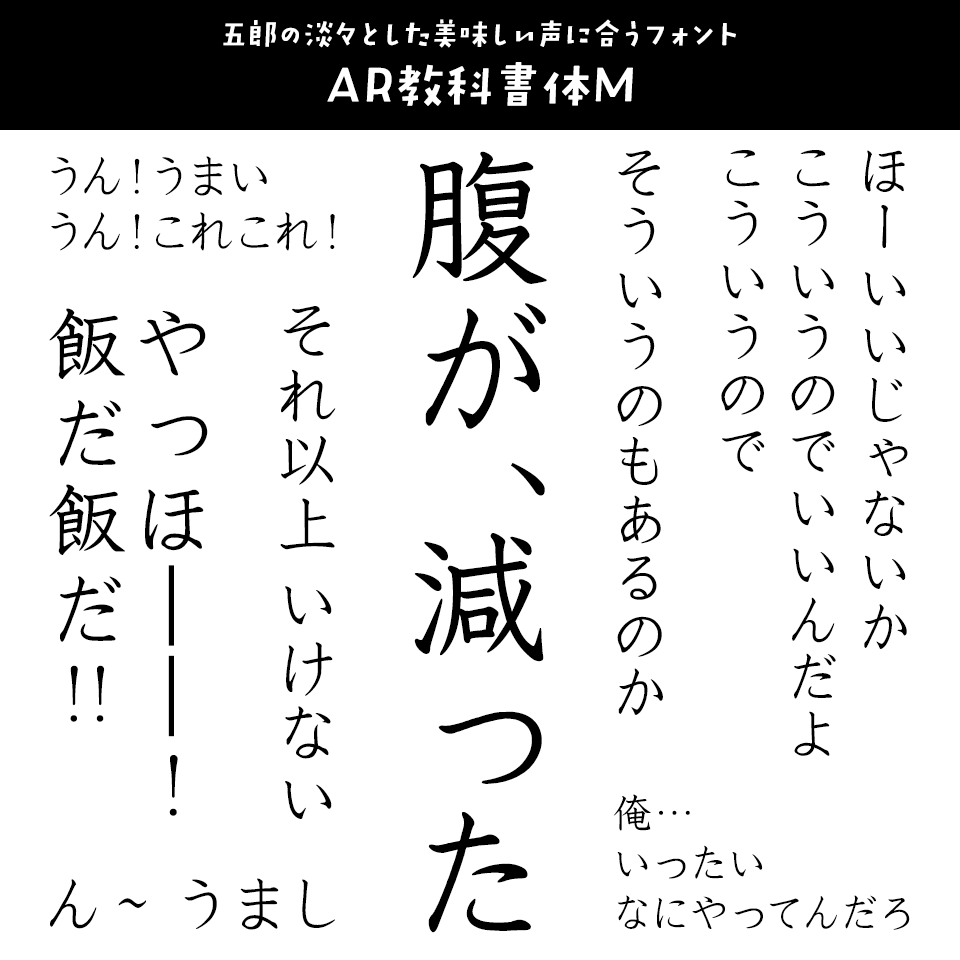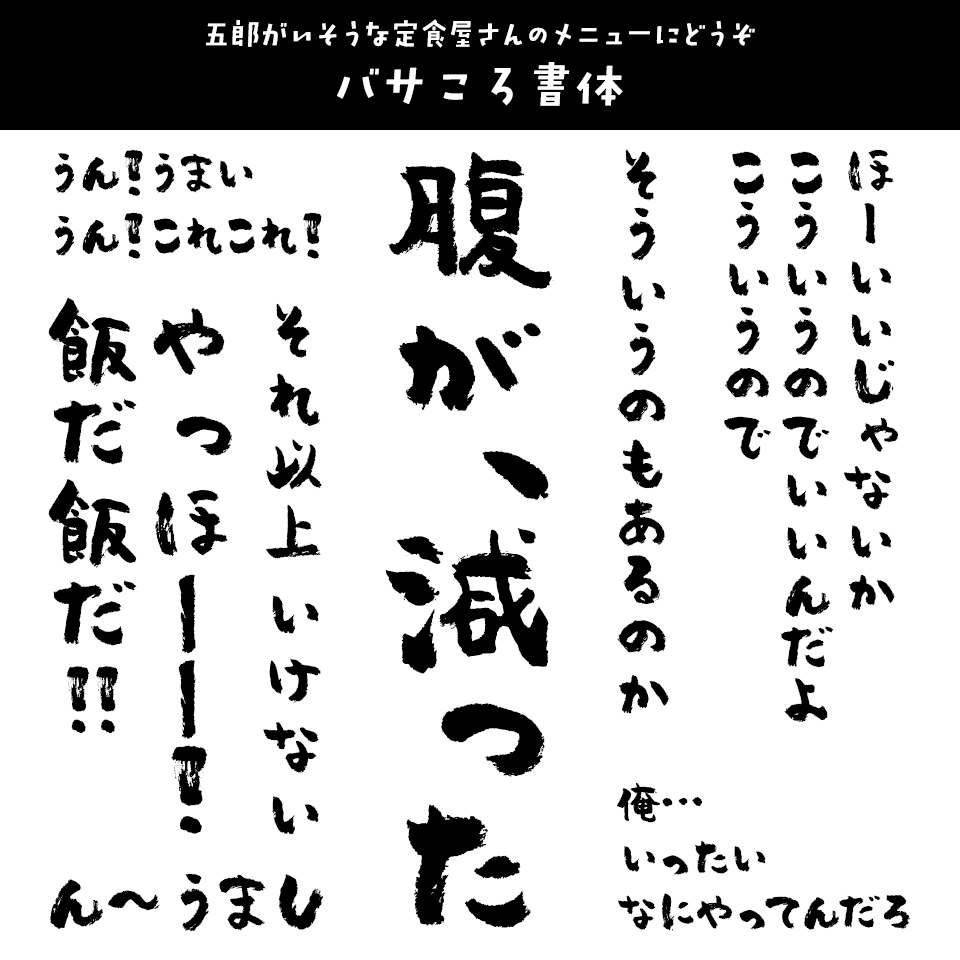
「孤独のグルメ」に合うフォント:特化型 目的別フォントガイド #116
今回は「孤独のグルメ」に合うフォント。日々フォントのことばかり考えている当店スタッフが直感的に選んだフォントをご紹介します。
「孤独のグルメ」に合うフォントをスタッフが選びました
「孤独のグルメ」に合うフォント ヒラギノ明朝 W3
コミックスで五郎の心の声で使われる明朝体
ヒラギノ明朝 W3【ヒラギノフォント】
「孤独のグルメ」に合うフォント ヒラギノ明朝 W3
現代的でシャープな表情の中に、伝統的な筆文字の美しさをマッチさせた華やかで上品な書体。起筆、送筆、収筆(とめ、はね、はらいなど)の各部に美しい筆づかいを取り入れつつ、日常的に使えるベーシックな明朝体として、デジタルならではの緻密さと一貫したデザイン性を持つ渾身の明朝体。
「孤独のグルメ」に合うフォント AR教科書体M
五郎の淡々とした美味しい声に合うフォント
AR教科書体M【アーフィック】
「孤独のグルメ」に合うフォント AR教科書体M
教科書でよく使用される、明朝体と楷書体の中間のデザイン。筆書きの楷書体に近く、明朝体のようにハネやはらいがありますが、線の太さの強弱は弱く、視力の弱い人にも見やすく読みやすい書体です。
「孤独のグルメ」に合うフォント マティス
力強いモノローグに
マティス【フォントワークス】
「孤独のグルメ」に合うフォント マティス
独特の重厚感のあるフォントでモノローグにもっと力強さと説得力を追加してみませんか。
「孤独のグルメ」に合うフォント DF唐風隷書体 W5
やや角ばった形の中にも素朴さが溢れだすフォント
DF唐風隷書体 W5【ダイナフォント】
「孤独のグルメ」に合うフォント DF唐風隷書体 W5
唐風隷書体 は、太く横長で扁平な字形が安定感をもたらし、中華風や古典的な雰囲気を演出するのにぴったりです。
「孤独のグルメ」に合うフォント DFクラフト遊 W5
どこかほのぼのとした印象の五郎の声に合う書体
DFクラフト遊 W5【ダイナフォント】
「孤独のグルメ」に合うフォント DFクラフト遊 W5
遊び心にあふれる子供が書いた文字をイメージしてデザインされた書体です。その為、文字のユニークさや破調が表現されたかわいらしい印象の書体になりました。短い点や線で構成された字形は軽やかさを感じさせ、陽気で活発な雰囲気が一層、引き出されています。
「孤独のグルメ」に合うフォント DFクラフト墨 W9
独特のこだわりを持つ五郎のセリフにぴったりの筆文字書体
DFクラフト墨 W9【ダイナフォント】
「孤独のグルメ」に合うフォント DFクラフト墨 W9
書道元来の構成や書き方に変化を加え、文字の面白さや破調を表現した書体です。線の長さや「へん」「つくり」などの部首に字形を崩す程の変化を加えました。また、空間の取り方も独特であり、丸く豊かな運びによって可愛く、リラックスした雰囲気を引き出され、ストロークからは墨字の躍動感が表現されています。
「孤独のグルメ」に合うフォント バサころ書体
五郎がいそうな定食屋さんのメニューにどうぞ
バサころ書体【昭和書体】
「孤独のグルメ」に合うフォント バサころ書体
かすれのあるゴロっとしたフォルムが温かみや親しみやすさを感じられる堅すぎない筆文字です。
「孤独のグルメ」に合うフォント 心龍爽
五郎と同じで細身で骨太
心龍爽【昭和書体】
「孤独のグルメ」に合うフォント 心龍爽
細めながらもしっかりとした毛筆体で、五郎のスタイルを連想させます。
「孤独のグルメ」に合うフォント DS筆七七
大衆食堂の雰囲気漂う筆文字風フォント
DS筆七七【七種泰史/デザインシグナル】
「孤独のグルメ」に合うフォント DS筆七七
粋な下町のオヤジさんのようなイメージをもって制作された書体。庶民的で温もりのある筆文字風フォントです。
「孤独のグルメ」に合うフォント 筆シリーズ TA筆くろもん
大衆食堂にありそうな手書き風フォント
筆シリーズ TA筆くろもん【スキルインフォメーションズ】
「孤独のグルメ」に合うフォント 筆シリーズ TA筆くろもん
あたかも誰かが手書きしたような少し崩れたリアル感が楽しい手書き風フォント。ゴシックデザイナー鈴木竹治のフォント。
「孤独のグルメ」に合うフォント 馬王顔書
手書き風だけどグイグイくる
馬王顔書【六葉情報】
「孤独のグルメ」に合うフォント 馬王顔書
五郎の心の声と同じで、控えめだけど主張の強い手書き風筆文字です。
「孤独のグルメ」に合うフォント 手書き屋本舗 竹ぱんだ
温かみのある手書き風フォント
手書き屋本舗 竹ぱんだ【スキルインフォメーションズ】
「孤独のグルメ」に合うフォント 手書き屋本舗 竹ぱんだ
強弱のついた手書きフォント。穏やかで五郎の声の温もりを感じます